CV’de hangi yazı tipi kullanılır: En İyi Yazı Tipleri + Font Seçimi Kılavuzu
CV yazılı bir metindir ve görünümündeki düzgünlüğün temelini tercih edilen font, font boyutu ve rengi oluşturur. İşe alım uzmanları üzerinde pozitif bir ilk izlenim bırakmak istiyorsanız, CV'nizin içeriği kadar görünümüne de önem vermeniz gerekir.
CV'de hangi yazı tipi kullanılır konulu yazımız içerisinde;
- Doğru yazı tipi seçiminin nasıl yapılacağını öğrenebilir,
- En iyi yazı tipleri listemizi gözden geçirebilir,
- Font büyüklüğü ve renk konularında bilmeniz gereken detayları inceleyebilirsiniz.
Öz geçmişiniz için en uyumlu yazı fontlarını açıklayarak yazımıza giriş yapalım.
CV için en iyi yazı fontları hangileridir?
Günümüzde kullanılan yüzlerce farklı yazı tipi bulunur. Ancak çeşitli yazı tipleri CV gibi iş başvurusu dokümanlarında keskin hatları ve okuma konforu yüksek görünümleriyle ön plana çıkar.
Temel font türlerini bilmek, doğru yazı tipi seçiminin kolayca yapılmasına yardımcı olur. Yazı tipleri genel olarak Serif ve Sans-serif olarak iki ana kategoriye ayrılır.
- Serif fontlar harflerin uçlarında yer alan küçük çizgiler sayesinde daha geleneksel ve resmi bir görünüm sunar. Bu yapı özellikle Garamond gibi fontlarda kendini gösterir ve metinlere klasik bir karakter kazandırır.
- Bu ek çizgileri barındırmayan Sans-serif fontlar daha sade, temiz ve modern bir görünüm sunar. Calibri gibi yazı fontları özellikle dijital ekranlarda okuma konforunu artırır.
CV'de hangi yazı tipi kullanılır sorusuna cevap olarak aşağıdaki tabloyu inceleyebilirsiniz.
Arial | Sade ve nötr yapısıyla profesyonel belgelerde en sık tercih edilen yazı tiplerinden biridir. Okunabilirliği yüksek olması sebebiyle CV'lerde güvenli ve risksiz bir seçim olarak kabul edilir. Modern ve dikkat çekmeyen yapısıyla içeriğin ön plana çıkmasını sağlar. |
Calibri | Microsoft Office’in varsayılan yazı tiplerinden biridir. Modern ve yumuşak bir görünüm sunar. CV’de hem ekran hem de baskı için dengeli bir okunabilirlik sağlar. Güncel ve profesyonel bir izlenim bırakmak isteyenler için ideal bir tercihtir. |
Courier New | Sabit genişlikli yapısıyla klasik daktilo görünümüne sahiptir. Genellikle teknik dokümanlarda tercih edilse de CV’de daha farklı ve dikkat çekici bir stil oluşturulmasına yardımcı olur. |
DejaVu Sans | Geniş karakter desteği ve temiz tasarımıyla özellikle dijital ortamlarda güçlü bir okunabilirlik sunar. Açık kaynaklı yapısı sayesinde farklı platformlarda tutarlı görünüm sağlar. Teknik olarak güvenilir olması ve sade bir izlenim sunması sebepleriyle CV'lerde tercih edilir. |
Garamond | Zarif ve klasik yapısıyla geleneksel bir görünüme sahiptir. Özellikle akademik ve resmi başvurular için kullanılan CV'lerde ciddi bir prestij oluşturulmasına yardımcı olur. |
Georgia | Güçlü okunabilirlik sunan yazı tiplerinden birisidir. CV’lere şık bir görünüm kazandırırken ciddi bir imajı da yansıtır. Modern ve dengeli tasarımıyla ön plana çıkar. |
Helvetica | Minimalist ve profesyonel görünümüyle ikonik yazı tipleri arasında bulunur. CV içerisinde net ve kurumsal bir görünüm oluşturur. Özellikle kurumsal alanlarda yapılan başvurularda güçlü bir tercih olarak öne çıkar. |
Poppins | Geometrik ve modern yapısıyla dijital çağın en popüler yazı tiplerinden birisidir. CV’ye çağdaş ve dinamik bir hava katarak özellikle yaratıcı alanlarda öne çıkmayı sağlar. Yuvarlak hatları sayesinde okuma konforu yüksek ve aynı zamanda estetik bir görünüm sunar. |
Mesleğiniz, bulunduğunuz sektör ve aradığınız iş pozisyonu kapsamında bu yazı fontlarını CV'nizde kullanabilirsiniz.
Farklı yazı tiplerinde CV örnekleri
Aşağıda, aynı CV şablonu içerisinde farklı yazı tiplerinin nasıl göründüğünü inceleyebilirsiniz:
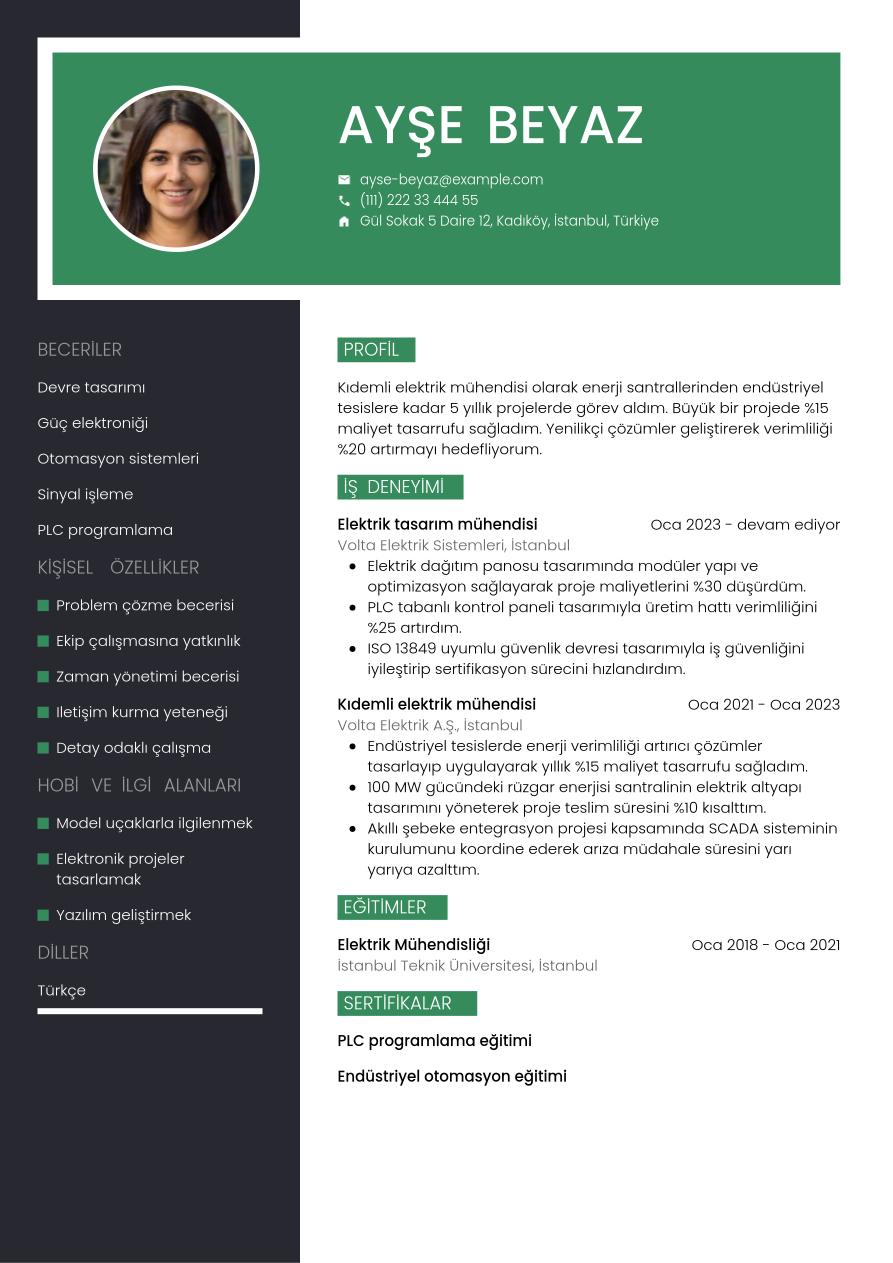
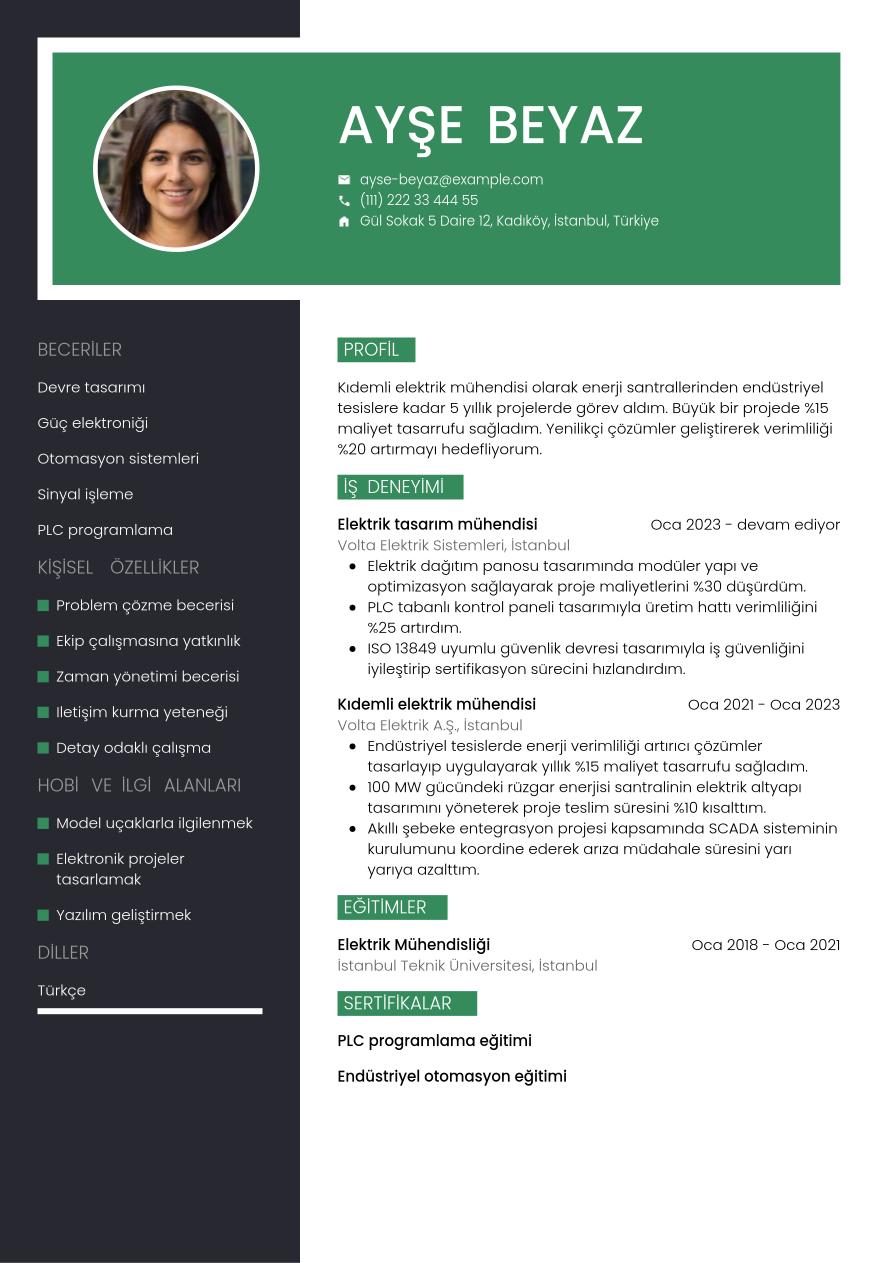
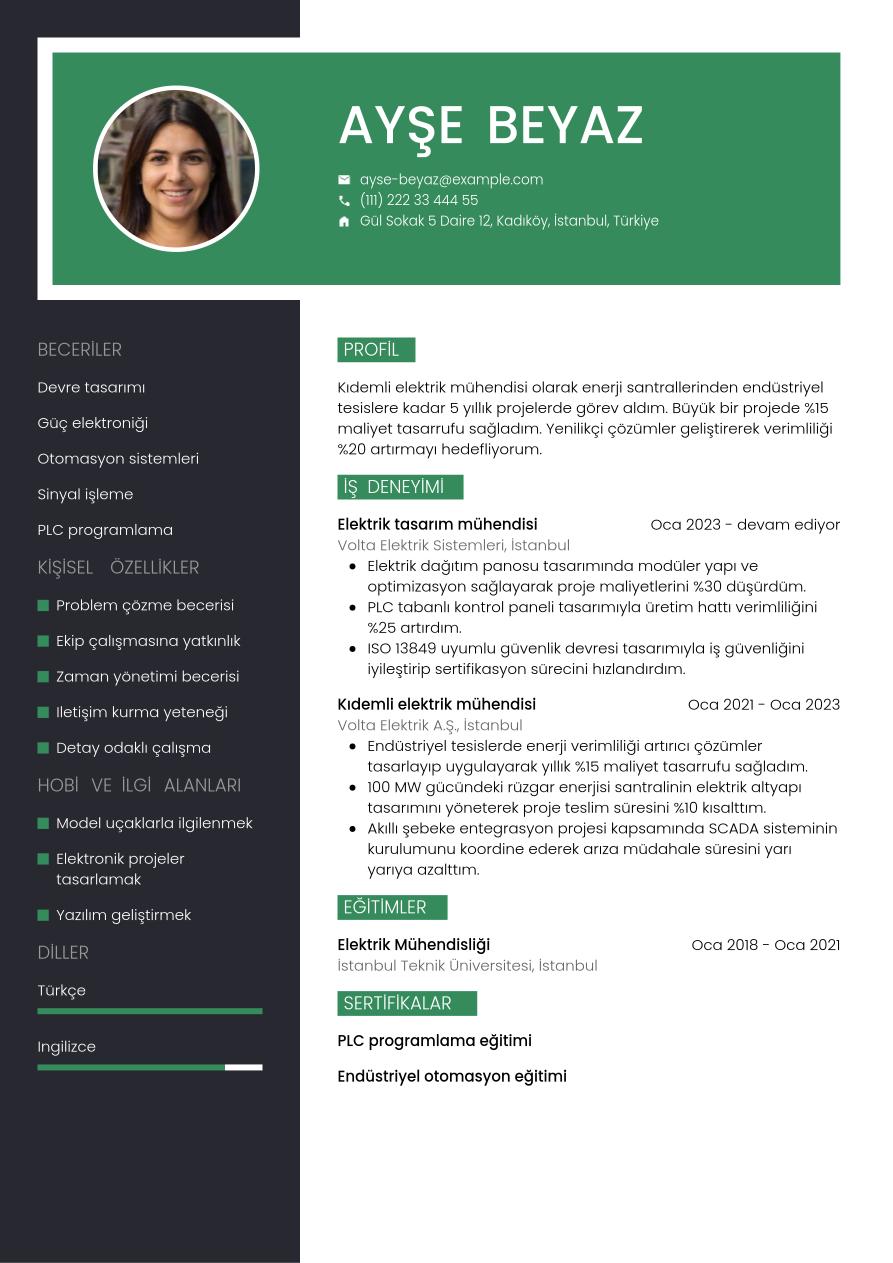
CV’niz için font seçerken bunlara dikkat edin
Öz geçmişinize en ideal fontu seçmek için kariyer rehberliği kapsamında hazırladığımız şu önerileri göz önünde bulundurun:
- CV yazı tipi ve boyutunu belirlerken okuma konforunu ön planda tutun.
- Hangi fontu seçeceğinize karar veremiyorsanız, en sade olan fonta yönelin.
- Seçtiğiniz yazı tipinde harflerin oldukça sıkışık veya fazla aralıklı olmadığından emin olun.
- CV'niz içerisinde tek bir yazı tipi kullanın. Farklı yazı tipi kullanmayı tercih ediyorsanız, başlık ve metinlerde uyumlu bir görünüm oluşturmaya özen gösterin.
- Font rengini siyah olarak seçin. Yaratıcı sektörlere iş başvurusu yapıyorsanız koyu renk tonlarını tercih edin. (Bu konuyu yazımızın devamında daha kapsamlı olarak ele alacağız.)
CV ve ön yazı şablonlarında doğru yazı tipi seçimi içeriği ön plana çıkarırken, tasarımı ise ikinci planda dengeli bir çerçeveye oturtur.
CV'de yazı puntosu kaç olmalıdır?
CV'de hangi yazı tipi kullanılır ve CV hangi yazı tipi ile yazılır soruları ile birlikte, genellikle yazı tipinin boyutu da merak edilir. Öz geçmişler için ideal font boyutu 10 ile 12 punto arasıdır. Ancak kullanılacak yazı tipi, font boyutu konusunda belirleyici bir rol üstlenir.